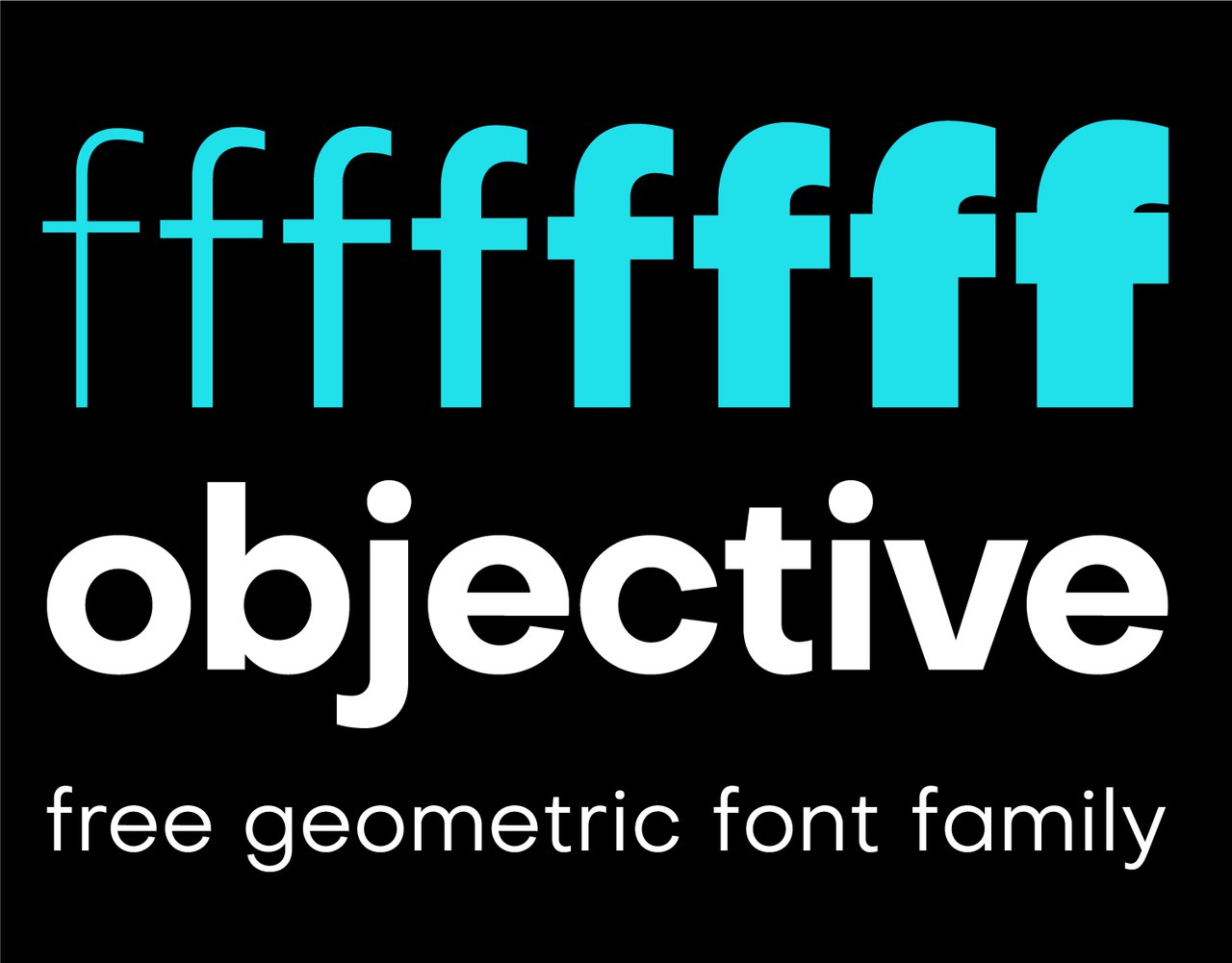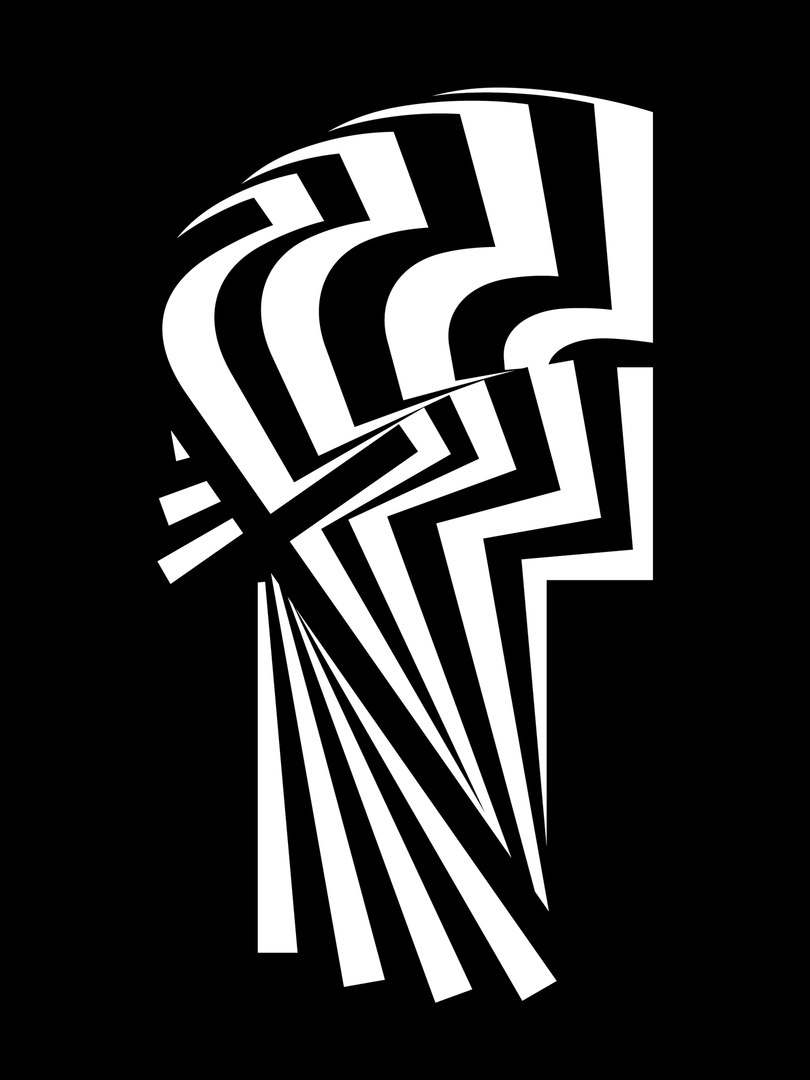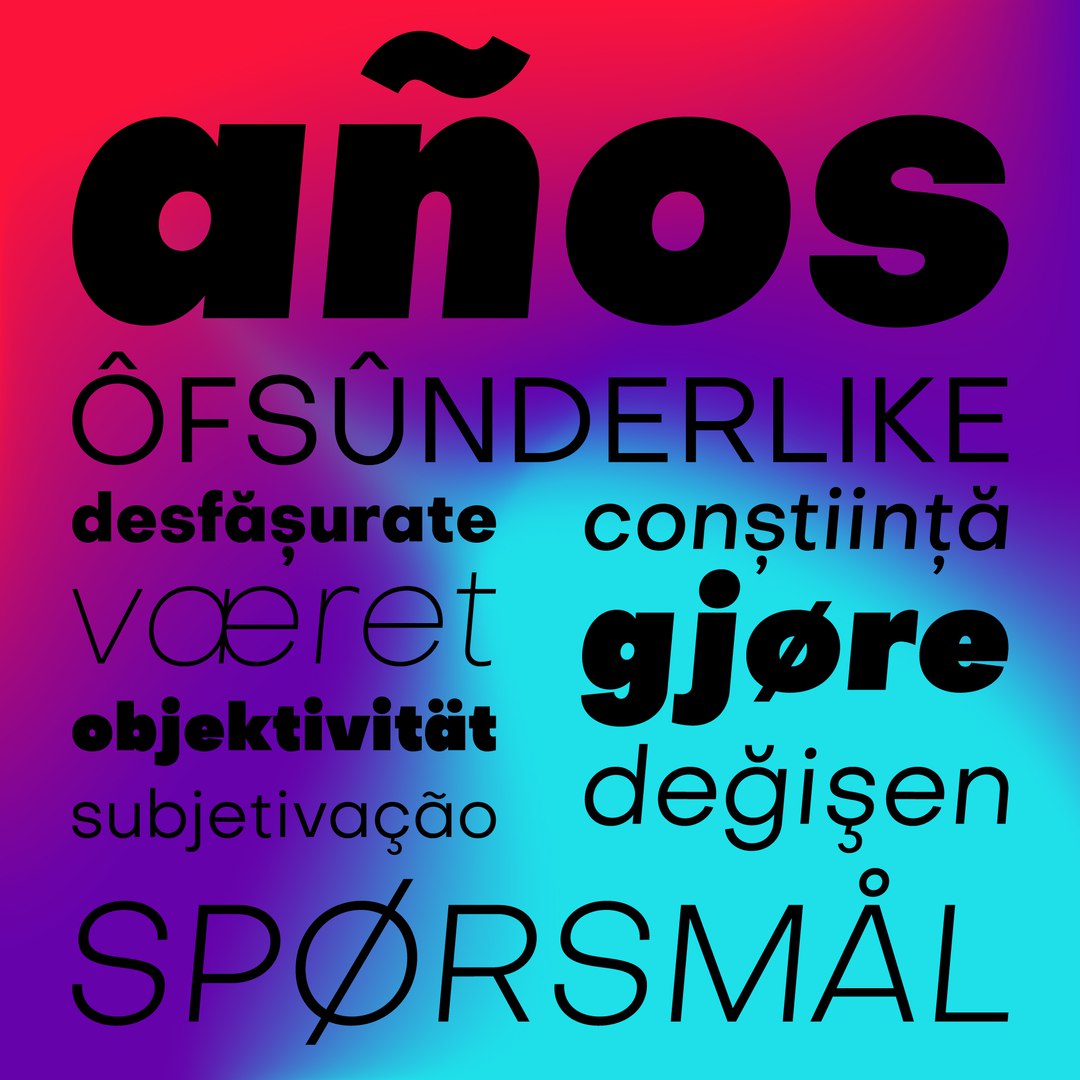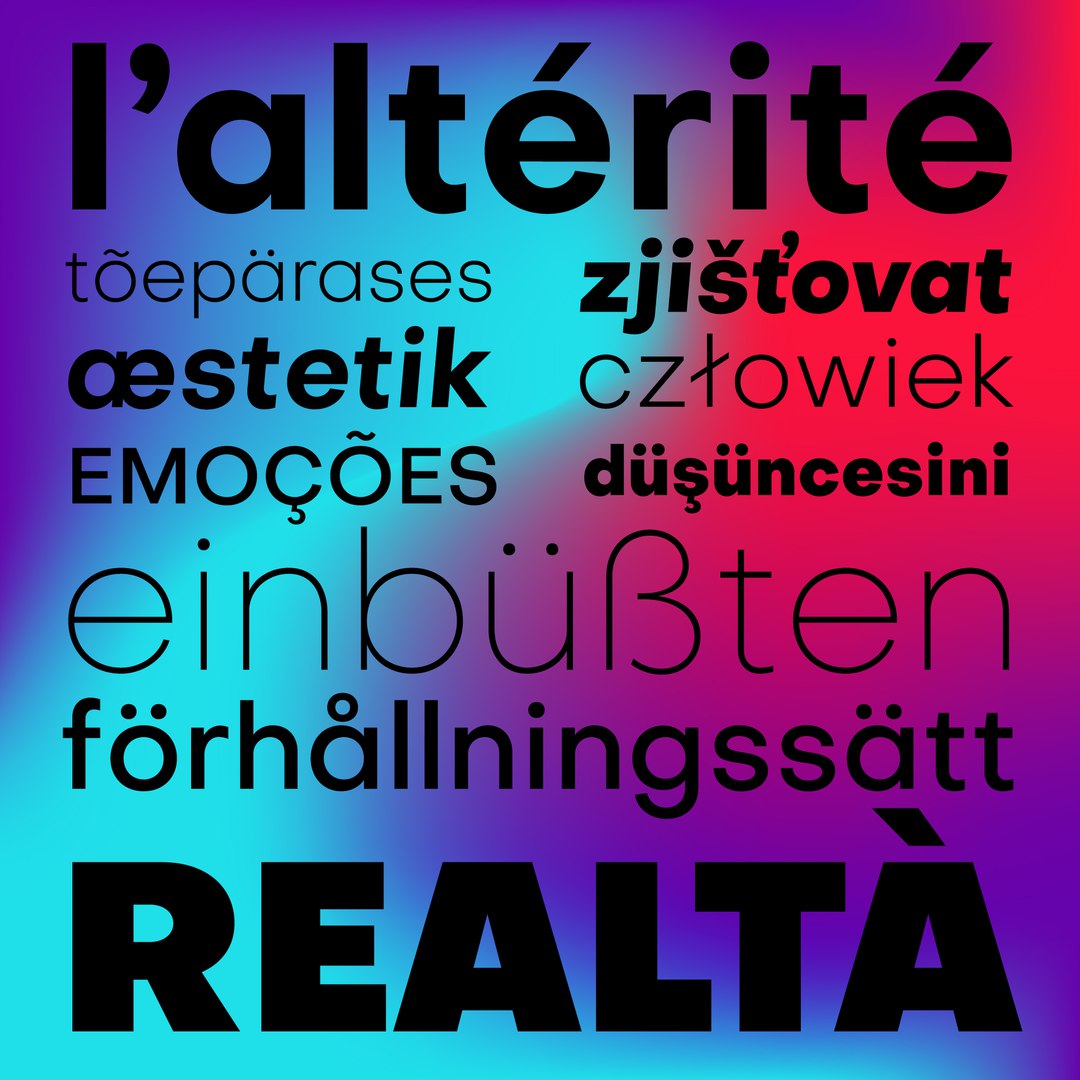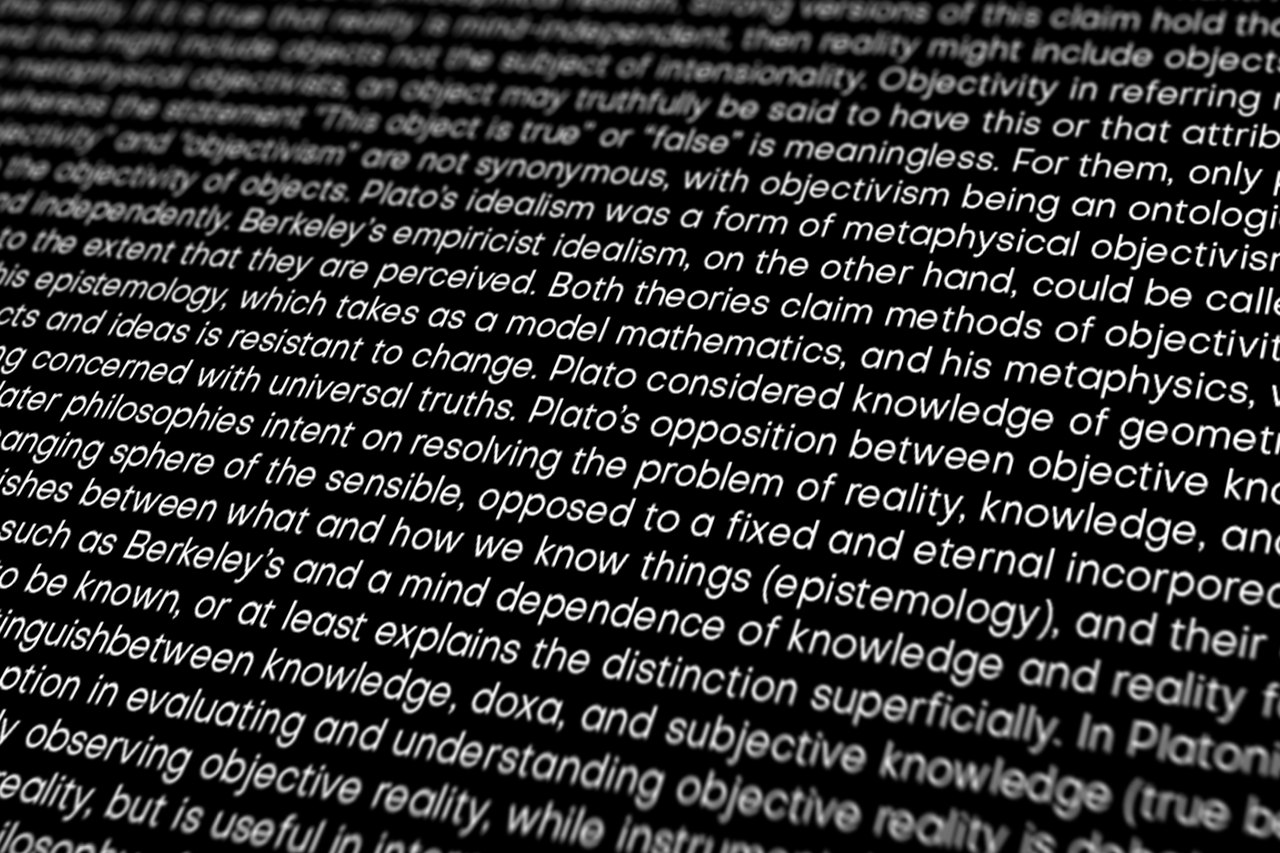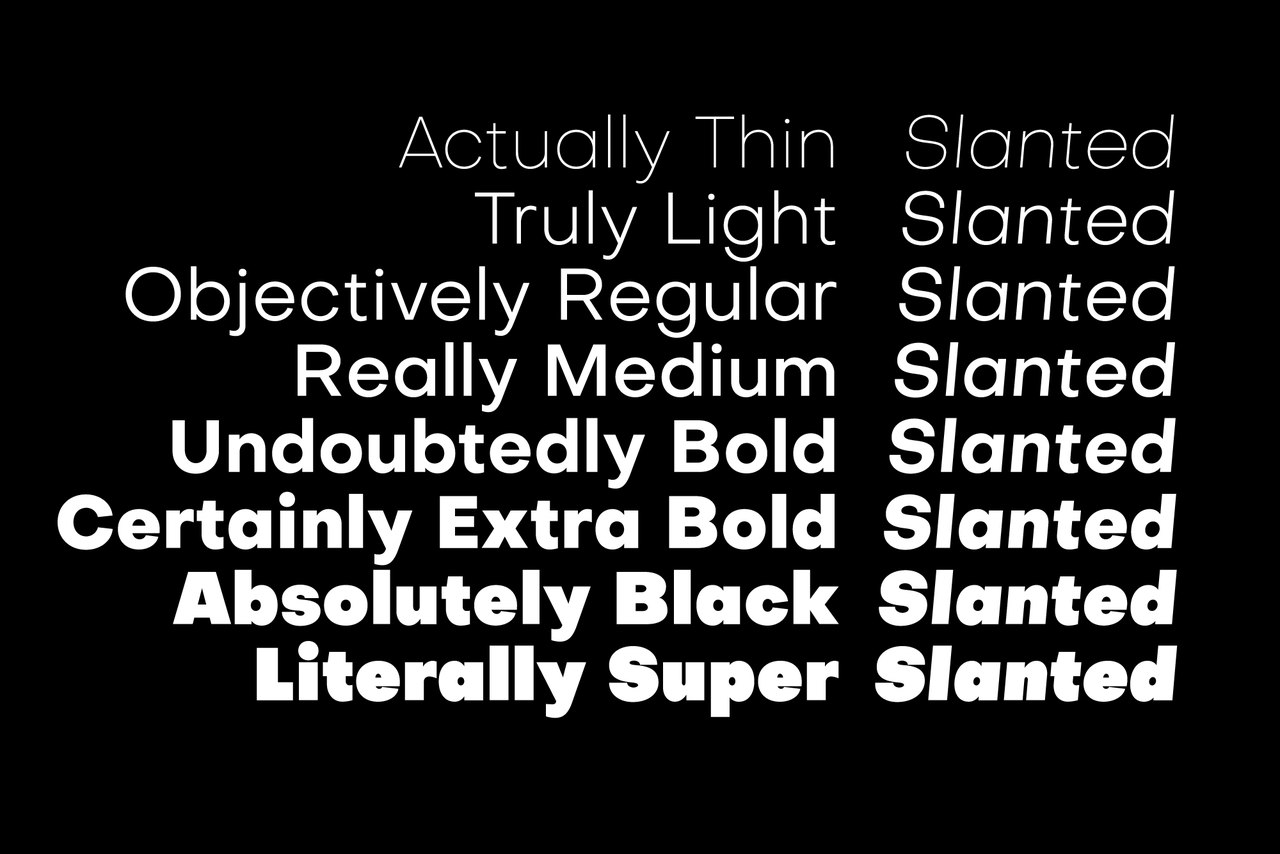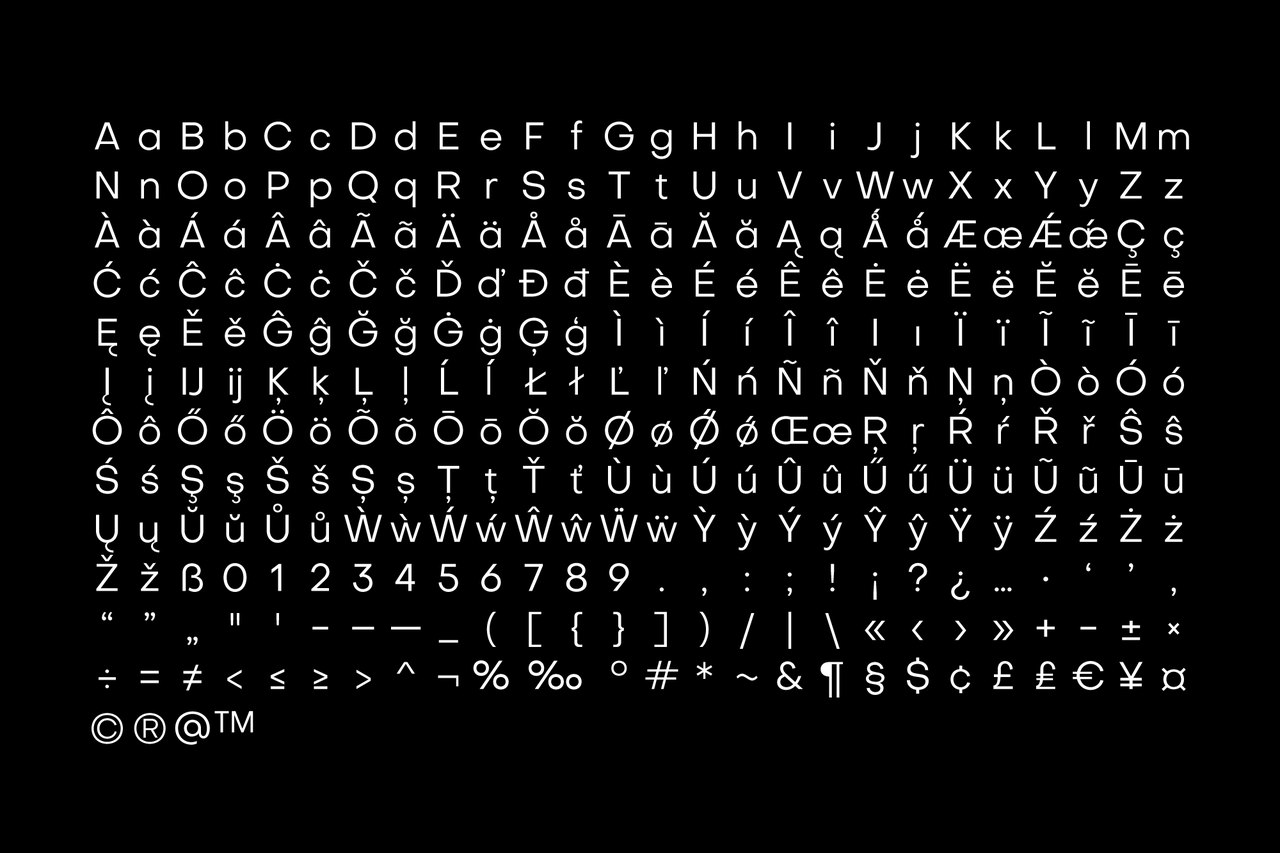
Современная геометрическая гарнитура Objective
Автор: Alexander Slobzheninov
“Objective это бесплатная геометрическая шрифтовая семья, открытая всему миру. Имя говорит само за себя – Objective объективный, чистый и нейтральный, это рабочая лошадка для самых разных проектов. Именно такой гарнитуры всегда нехватало лично мне. Как и полагается универсальным шрифтам, тут есть 8 начертаний от тонкого до супержирного + наклонные, 347 глифов в каждом, 192 языка (латиница). Вебфонты в комплекте. Если есть желающие нарисовать кириллицу, или проспонсировать ее, пишите)”